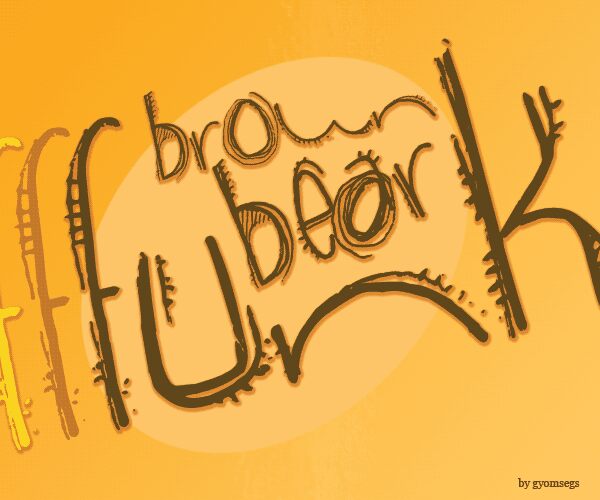
Brown Bear Funk to krój w stylu trash, który wygląda, jakby został wydrapany na papierze nerwowym ruchem długopisu. Każda litera jest cienka, kudłata i niespokojna, z nakładającymi się liniami, które sprawiają wrażenie odręcznych i nieco szalonych. Luźne, zapętlone formy nadają tekstowi surową energię DIY, jakby pochodził prosto z kserowanego zina lub ściany tagowanej markerem.
Dzięki Brown Bear Funk Twoje nagłówki natychmiast zyskują zadziorny, podziemny charakter, który przykuwa wzrok. Ten darmowy font świetnie sprawdza się na plakatach koncertowych, okładkach zinów, grafikach skate i streetwear, w tytułach horrorów czy komedii, na okładkach albumów oraz w odważnych grafikach do social mediów. Stosuj go w dużym rozmiarze dla lepszej przejrzystości i zestawiaj z prostym, wąskim krojem bezszeryfowym, aby okiełznać ten chaos i zachować czytelność.